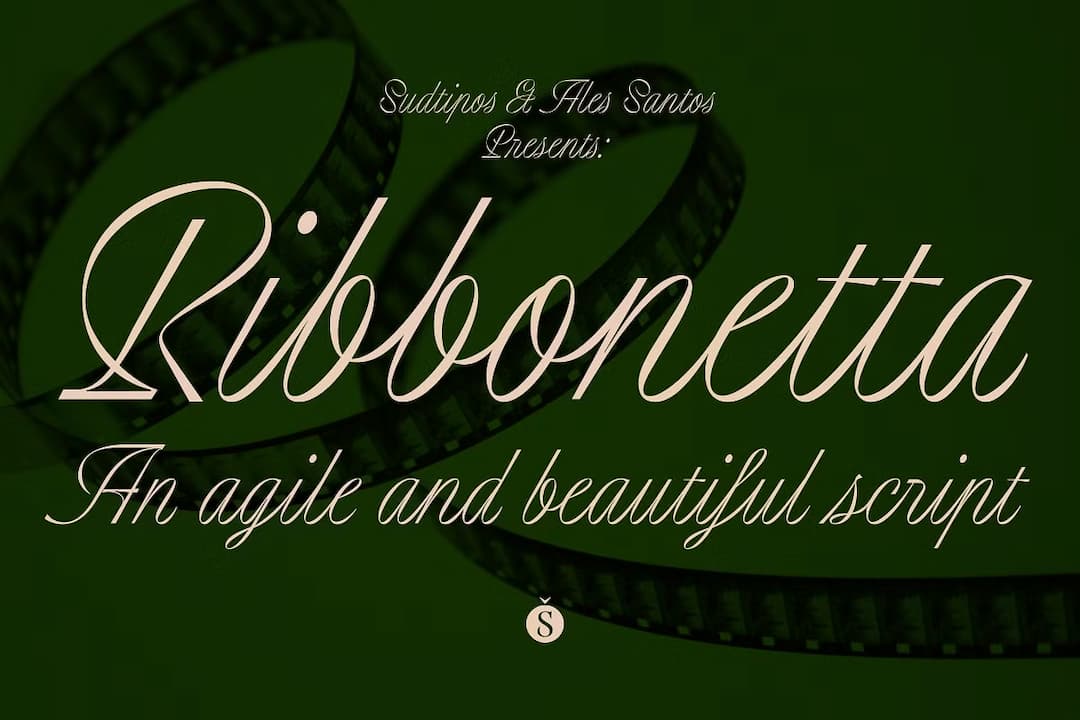
Ribbonetta
レトロでチャーミングでエレガントなスクリプト。名前の通り細いリボンのようなストロークが特徴的なスクリプトで、20世紀中頃までに登場した活字タイプのスクリプトにこのようなものがあったが、それらは文字同士のコネクションが取られていなかった。この書体は普通のスクリプトのようにちゃんと繋がっている。全体的にややコンデンス気味で、xハイトが大きめなのも気取りすぎておらず可愛らしい。スワッシュオルタネートは豊富にある模様。年末のプレゼントシーズンにいかが。1ウェイト。